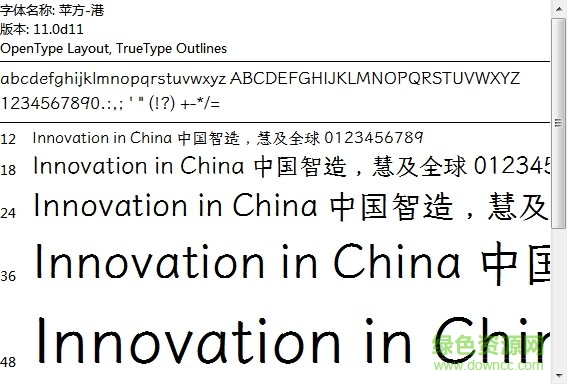
寧?kù)o之雨字體是ios9系統(tǒng)線刷包字體合集,共39款字體,是微信公眾號(hào)寧?kù)o之雨修改過(guò)后的蘋方字體系列,喜歡的朋友歡迎來(lái)綠色資源網(wǎng)體驗(yàn)哦!
クレPro字體由寧?kù)o之雨翻新了這款2015年的很漂亮的字體,蘋果安卓都有中英文替換。
也是寧?kù)o之雨公眾號(hào)上很多小伙伴一直想要的一款字,花了不少時(shí)間重做的。
用思源黑重新擴(kuò)充了安卓版的字庫(kù),移植了英文數(shù)字;
增補(bǔ)S7缺失的droidsansfallback(自制版,以小塚黑補(bǔ)思源黑而成),保證替換字體字符缺失時(shí)可以回退調(diào)用
開啟中文字體多字重調(diào)用,而不是程序渲染偽粗偽細(xì),在2K屏下粗細(xì)字體效果顯著(可能我已經(jīng)養(yǎng)成像素眼了)
修復(fù)谷歌原生字體打底制作導(dǎo)致S7撥號(hào)鍵盤星號(hào)鍵亂碼問(wèn)題
西文替換為方正在蘭亭Pro里最新推出的那套字體,多字重,自制斜體